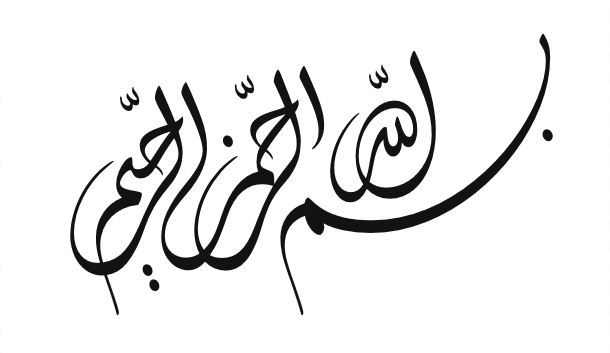
فونت طلایی الذهبی
فونت طلایی الذهبي یا الذهبي یکی از فونت‌های خانواده طلایی الذهبي شرکت مایکروسافت است. که از یک وزن معمولی (regular) برای پلت فرم ویندوز با فرمت فونت عربی True type تشکیل شده ات. که کاربرد آن بیشتر برای اندازه‌های کوچک مانند فونت دسکتاپ و لینک‌ها و آیکون‌های و در کل رابط‌های کاربری ویندوز است که البته برای زبان فارسی بهترین فونت برای استفاده در مرورگرها هم هست.فونت عربی نستعلیق طلایی با نام لاتین Aldhabi  و نام عربی الخط الذهبي شهرت دارد فونتی بازمانده از سال 2017 هم اکنون منتشر به درخواست شما منتشر شده فونتی با رنگ و لعاب ثلث با بوی نستعلیق نویسی ، در سه زبان عربی فارسی ( دارای کچ پژ ) و لاتین می باشد.
در کجا میتوان از فونت عربی نستعلیق طلایی استفاده کرد؟